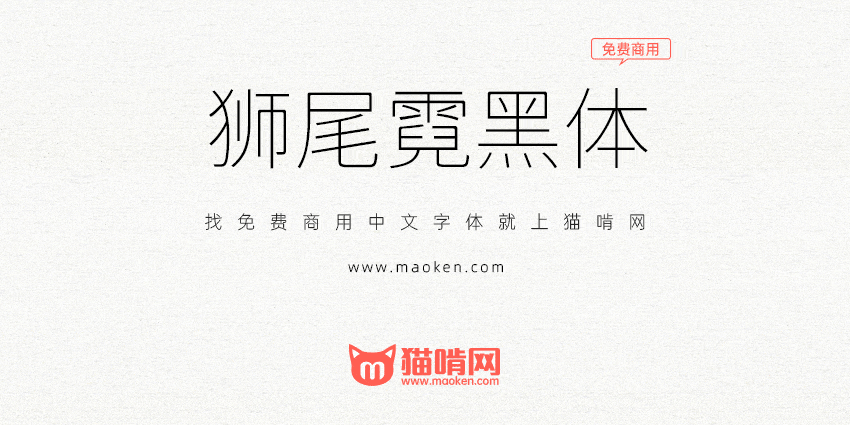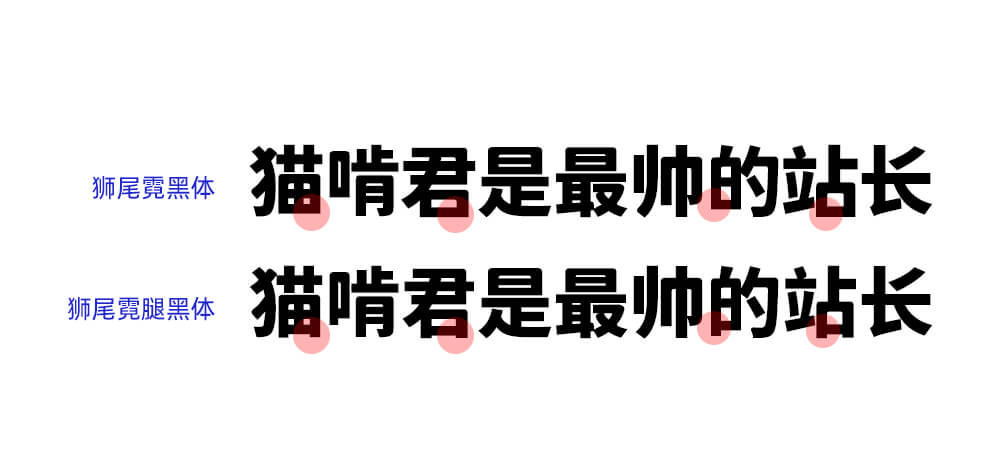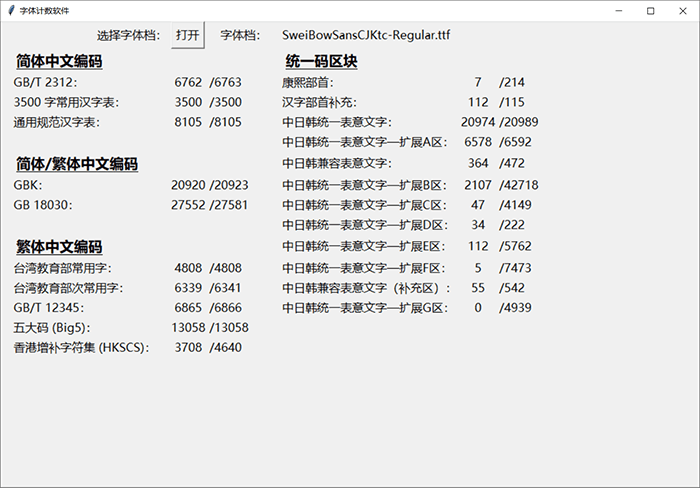
狮尾霓黑体基于思源黑体的上半边变圆和拔脚改造,更加简明现代化的字体。支援简体中文、繁体中文、韩文与日文;欢迎大家自由应用、自由优化、自由改作!
狮尾霓黑体的特色是,上半边圆体+下半边黑体,一个综合的字体,「口」字的上沿有一点点像彩虹形状。
「狮尾霓黑体」与「狮尾霓腿黑体」差别在有没有拔脚,「拔脚」就是会有较少的笔画,例如移除「口」字的左右下角会多出的短线条。有拔脚的字会较圆,但是会造成有些字因直接去掉腿后左右不平衡、左右不对衬的「悬空」问题。改使用「腿」系列字体就不会有这个问题。